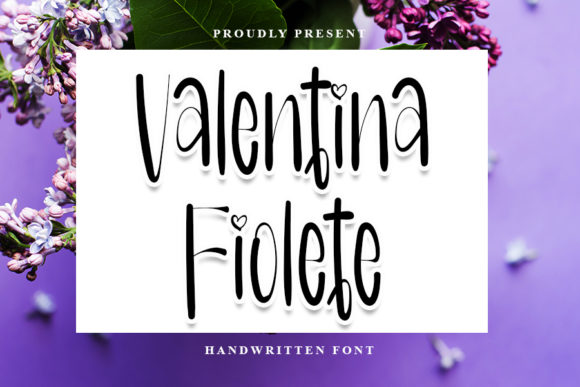
Valentina Fiolete
適切なデザイン要素を見つけるのは難しい場合がありますが、Valentina Fioleteは作品を即座に引き立てる優れたコレクションを提供します。
POD(オンデマンド印刷)製品、結婚式の招待状、またはソーシャルメディアのグラフィックを作成している場合でも、Valentina Fioleteは理想的です。